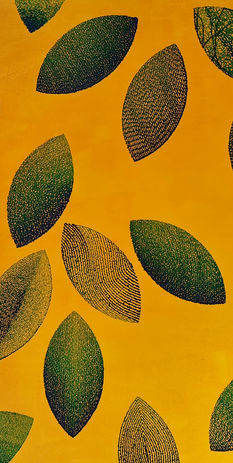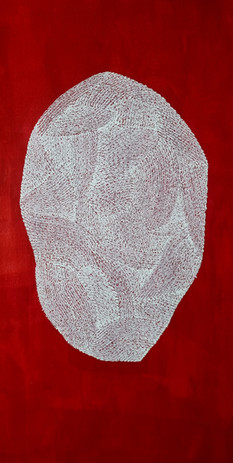
Pierre Bonorden
Was bewegt Menschen, was treibt sie an und wie treffen sie Entscheidung und warum manchmal halt nicht?
Nach Jahren des Tagebuchschreibens trieb mich diese Frage Ende der neunziger Jahre auf den ersten großen Papierbogen.
Auf ihm notierte ich unzusammenhängende Zitate, Sprüche und Bemerkungen. Anschließend begann ich die Verbindung zwischen den Sätzen zu suchen, zog Linien, beschrieb diese und fand Strukturen, Muster, Zusammenhänge.
Bis heute entstehen meine Bögen aus Fragen des menschlichen Miteinanders, den Sehnsüchten, Wiedersprüchen und Spannungsfelder, die uns als Menschen beschäftigen, definieren, die uns erfreuen und bewegen.
Hierbei sind es nicht nur die Interaktion zwischen den Menschen, sondern auch die internen Fragen und Wiedersprüche, die sich oft nur in den kleinen Gesten und Nebensätzen finden, die den Bögen ihre Form geben.
Aus dem Tagebuch kommend, entstehen die Bögen ausschließlich mittels Handschrift, Tinte und Feder oder Pinsel und immer direkt, aus einer Frage, einer Beobachtung, einem Gefühl das es zu greifen gilt, es gibt keine Skizzen vorab. Und wie im Tagebuch entstehen die Sätze beim Schreiben, beim Treibenlassen auf und in einem Gedanken, einer Struktur die es gilt zu verstehen.
Oder es sind einzelne Wörter, die wiederholt werden, wie ein Bogen über das Wort HALT, das wohl den stärksten Wiederspruch in sich trägt den ich bei einem Wort bisher erfahren habe.
Es gab auch eine Zeit, in der ich mich an Texten versuchte und schrieb, aber irgendwie ist ein Bild aus Wörtern, das Schriftbild, für mich bis heute ausdruckstärker und direkter und der Moment des Entstehens mir näher als der Satz hinter einem Statz….
Und so möchte ich beim SchriftArtFestival meine Schriftbilder teilen, mich mit meiner Kunst einen weiteren Schritt hinauswagen und vielleicht auch zeigen, dass Schrift mehr ist, als nur Wörter und Interpunktion, sondern Genuss, Kreativität, Schönheit und Vielfalt, möchte gerne ein Teil dieser Schriftkunstschaffenden sein, in der Hoffnung für Schrift zu begeistern!